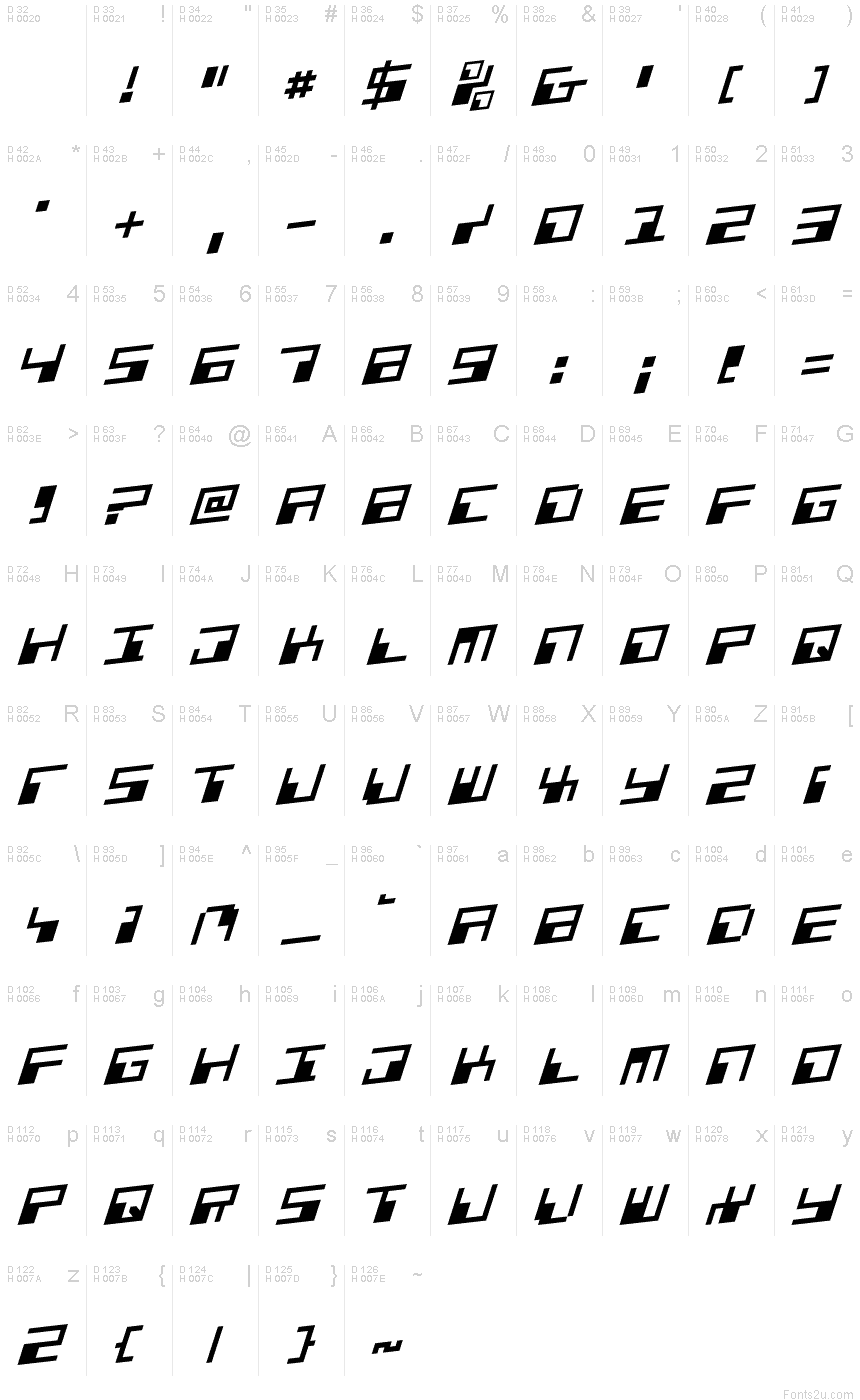
Phaser Bank Rotalic od Iconian Fonts to darmowy, futurystyczny font techniczny (wielkie litery), wyróżniający się dynamicznym nachyleniem i ostrymi, ściętymi kątami. Litery sprawiają wrażenie szybkich i zaprojektowanych z inżynierską precyzją, a szerokie pociągnięcia cięte w kliny nadają całości klimat logo sci-fi, daleki od neutralnych fontów wyświetlanych.
Ten darmowy font idealnie pasuje do brandingu gier, ulotek muzyki elektronicznej, nagłówków plakatów, plansz tytułowych oraz oprawy wydarzeń technologicznych, gdzie tekst musi mieć w sobie dynamikę. Świetnie sprawdza się też w tekstach okładkowych i monogramach, ponieważ wielkie litery łączą się z napięciem, nadając nawet krótkim wyrazom wyrazistego charakteru.